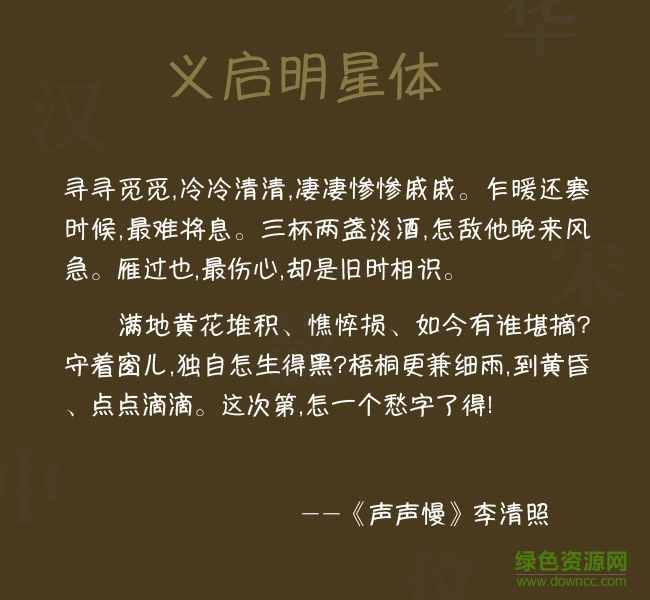
義啟明星體字體是一款義啟類圓滑風(fēng)格字體軟件,明星體在筆畫上盡顯隨意自由的風(fēng)范,整體效果給人很大的遐想空間,字體間連接嚴(yán)謹(jǐn),是很多年輕人和書法家比較喜愛的一類字體,感興趣的朋友歡迎來綠色資源網(wǎng)下載體驗!
“追星”這個詞對于80、90甚至00后來說應(yīng)該一點也不陌生,不管中國的,韓國的還是歐美的明星,總有很多人去追。義啟明星體”,來表達(dá)自己追星的情感。義啟明星體在用筆和結(jié)構(gòu)方面給與作者很大的想象空間。明星體筆畫呈上弓形,圓潤而有張力。結(jié)構(gòu)平實而拙中見巧,字字間的處理嚴(yán)謹(jǐn),筆畫順勢而為而個性十足。